Nouvelle police de code
La nouvelle police de code est une police plus légère, moderne, sans empattement, adaptée aux écrans haute résolution.
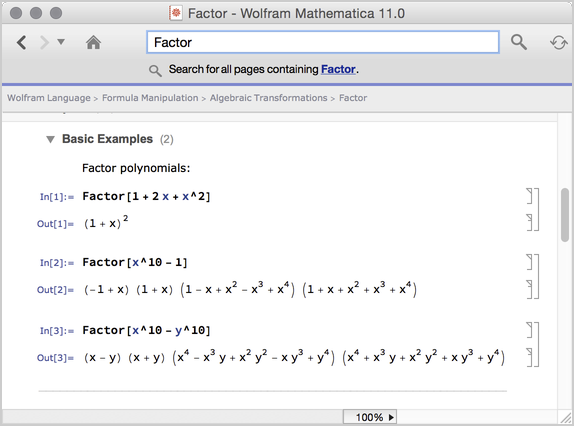
La police de code précédente en guise de comparaison.
La nouvelle police de code est une police plus légère, moderne, sans empattement, adaptée aux écrans haute résolution.
La police de code précédente en guise de comparaison.